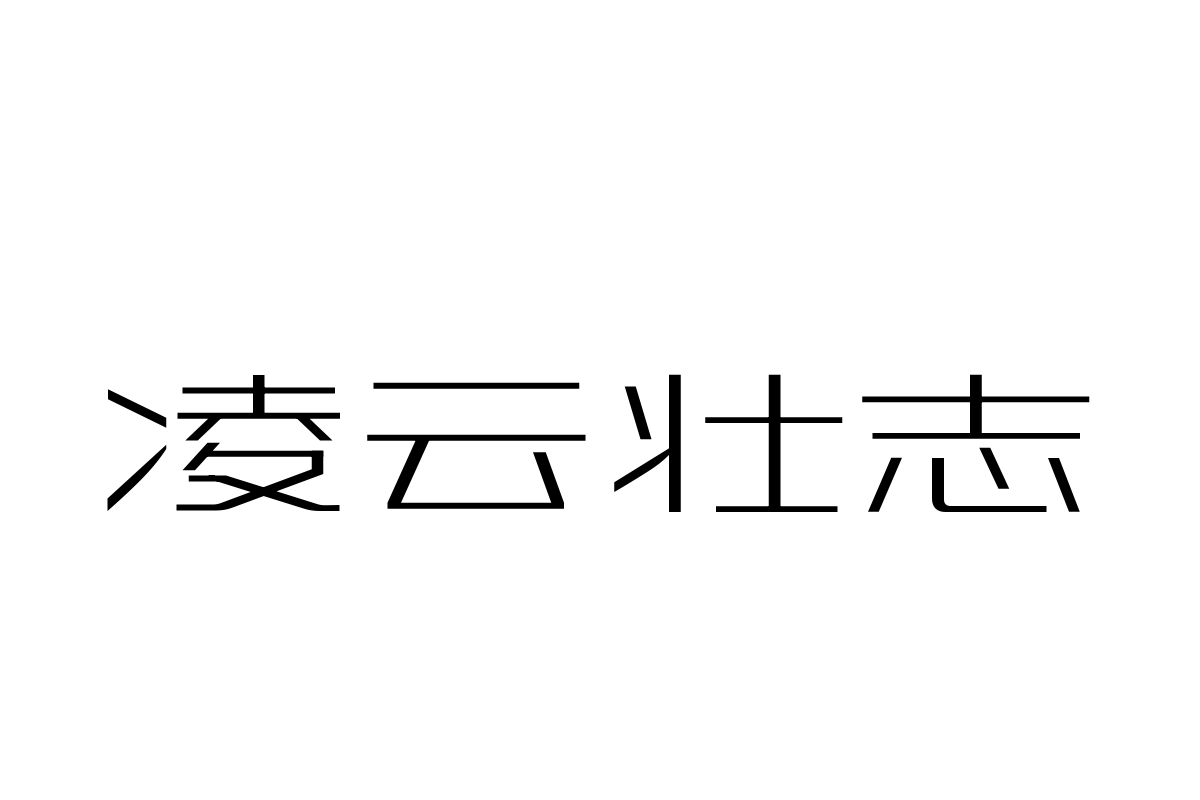
三极刃黑 纤细字体是一款具有现代感的无衬线字体,其特点是简洁、清晰和易读。这款字体的设计灵感来源于传统的书法艺术,但又在笔画的处理上进行了创新,使其更加符合现代审美的需求。
三极刃黑 纤细字体的特点是:
1. 笔画流畅:该字体的笔画线条平滑,没有过多的转折,使得整体看起来更加流畅自然。
2. 字形均衡:每个字符的间距和大小都保持均匀,使得整个字体看起来更加协调。
3. 易于识别:由于其简洁的设计风格,三极刃黑 纤细字体非常易于识别,无论是在印刷品还是电子屏幕上都能清晰地显示。
4. 适应性强:这款字体适用于各种类型的文本,包括标题、正文、广告等,具有很强的适应性。
总的来说,三极刃黑 纤细字体是一款非常适合现代商业和创意设计需求的无衬线字体。